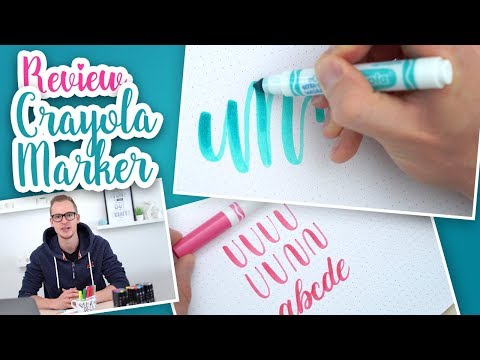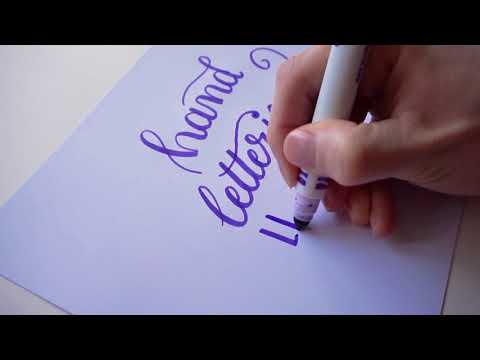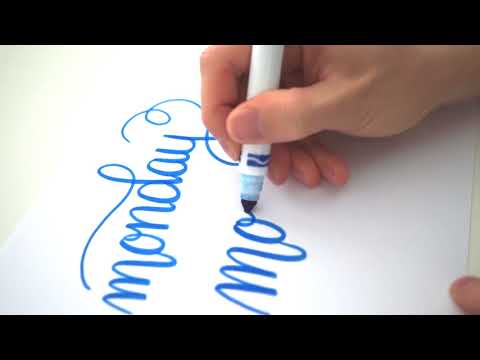
Eine äußerst günstige Alternative zu anderen Brush-Pens sind die Marker von der Firma Crayola.
Die Stifte sind eigentlich für Kinder gedacht und daher auswaschbar und eben sehr günstig.
Zufälligerweise verfügen sie aber auch über eine Spitze, mit der du sowohl feine als auch dicke Linien malen kannst. Damit eigenen sie sich perfekt für das Handlettering!
Handlettering mit Crayola Markern
Für mich ist natürlich am wichtigsten, wie gut sich die Marker als Handlettering Stifte eignen.
In der Handhabung sind sie etwas anders, als echte Brushpens. Statt einer Pinselspitze haben die Crayola Marker eine Art Farbkissen.
Dieses Farbkissen ist, genau wie eine Pinselspitze, drucksensitiv. Das heißt bei viel Druck entsteht ein dicker Strich und bei wenig Druck ein schmaler Strich.
Der Bereich zwischen leichtem Druck und stärkerem Druck ist recht schmal und erfordert daher Übung und Feingefühl. Auch der passende Winkel ist bei den Crayola Markern besonders wichtig.
Hast du den Dreh aber erstmal raus, wirst du die Stifte lieben lernen!
Da das Farbkissen extrem robust ist, brauchst du nicht auf die Schreibrichtung achten und kannst sogar auf rauerem Papier schreiben. Auch für Linkshänder sind die Marker übrigens eine fantastische Alternative.
Ich benutze sie auch gerne um einfach komplett spontan auf einer „endlos“ Papierrolle zu lettern und mich von den Stiften leiten zu lassen.
Auch für ein schnelles Lettering zwischendurch eigenen sich die Marker super. Ich kann mittlerweile total verstehen, warum viele Handlettering Künstler so begeistert von diesen Stiften sind.
Video-Beispiele
Hier habe ich noch zwei Videos für dich, wie ich die Crayola Marker für ein Lettering einsetze:
Für Einsteiger geeignet?
Zum kompletten Neueinstieg würde ich weiterhin die Brushpens von Edding empfehlen aber als zusätzliche Ausrüstung sind die Crayola Marker perfekt geeignet.
Vielleicht liegt dir das Schreiben mit den Markern auch besonders gut und du möchtest gar keinen normalen Brush-Pen mehr benutzen? Ein Versuch ist es auf jeden Fall wert, da die Stifte so günstig sind.
Kinderkram
Wie oben bereits angerissen sind die Crayola Marker auch perfekt für Kinder geeignet.
Sei es, um mit dir zusammen zu lettern (Kinder lassen sich ganz schnell vom Handlettering begeistern) oder einfach als Filzstifte zum ausmalen von Bildern.
Die robuste Spitze verzeiht den noch etwas gröber agierenden Kinder-Händen fast alles und die Farbe ist auswaschbar. Was will man mehr!?
Blending mit Crayola Markern
Da die Crayola Marker auf Wasserbasis sind (und damit übrigens auch auswaschbar), lassen sich die Farben sogar ein wenig überblenden. Damit kannst du Letterings mit tollen Farbverläufen erstellen.
Um die Farben zu vermischen musst du mit einer Farbe auf etwas glattem, wie zum Beispiel Glas oder Folie, etwas Farbe auftragen.
Mit der zweiten Stiftspitze nimmst du diese Farbe auf und fängst an zu Lettern. Nachdem die aufgenommene Farbe langsam abnimmt, kommt die Original-Farbe des Stiftes wieder durch.
So entsteht ein schöner Verlauf – das sogenannte „Blending.“
Es geht aber auch ohne diesen „Umweg“. Einfache Verläufe lassen sich auch durch direktes Übermalen erzeugen. Hierbei ist dickes Papier umso wichtiger.
Review im Video
Ich denke, damit hast du einen guten Eindruck von den Crayola Markern bekommen. Nun ist es Zeit, dass du selbst einen Test wagst.
Ich finde die ganz prima. Aber ich tute mich sehr schwer mit ihnen zu schreiben. Das gelingt mir nicht wirklich. Man muss so aufpassen, dass man den Stift im richtigen Winkel hält. Aber das ist bestimmt auch nur eine Frage der Übung.
Hey Doro, ja das mit dem Winkel ist wohl die Crux bei der Sache. 🙂 Aber ansonsten mag ich die Crayolas auch immer mehr …